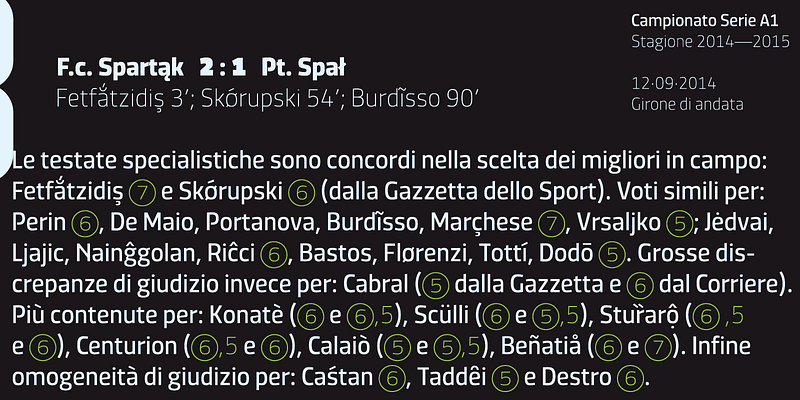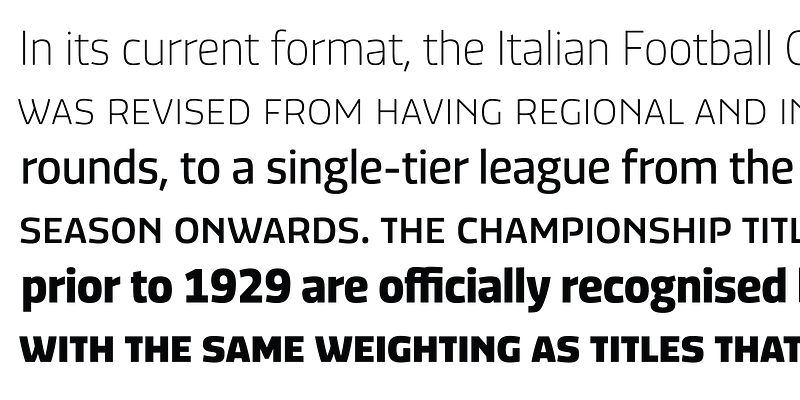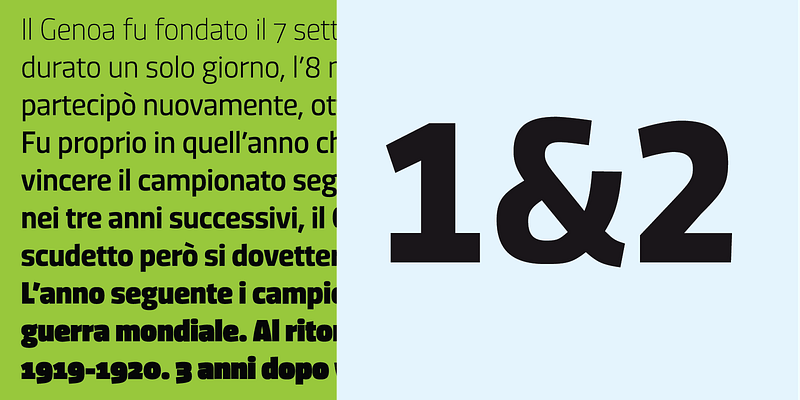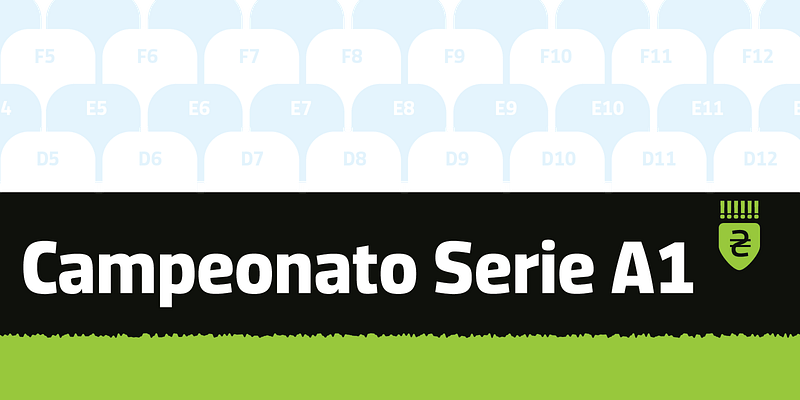
Dic Sans は多くのウェイトが用意されているスクエアサンセリフ体で、画面上でも印刷でも見栄えがします。開口部が広く幾何学的でないデザインになっている、Novarese の Eurostile からアイデアを得ています。
Cooperativa Anonima Servizi Tipografici (略称 CAST) は、独立系デジタル書体フォントメーカーです。イタリアのボルツァーノに協同組合として設立されました。現代デザインコミュニティで積極的に活動し、強力なビジュアルアイデンティティを求めるコミュニケーションプロフェッショナルや企業にとって頼りになる存在です。